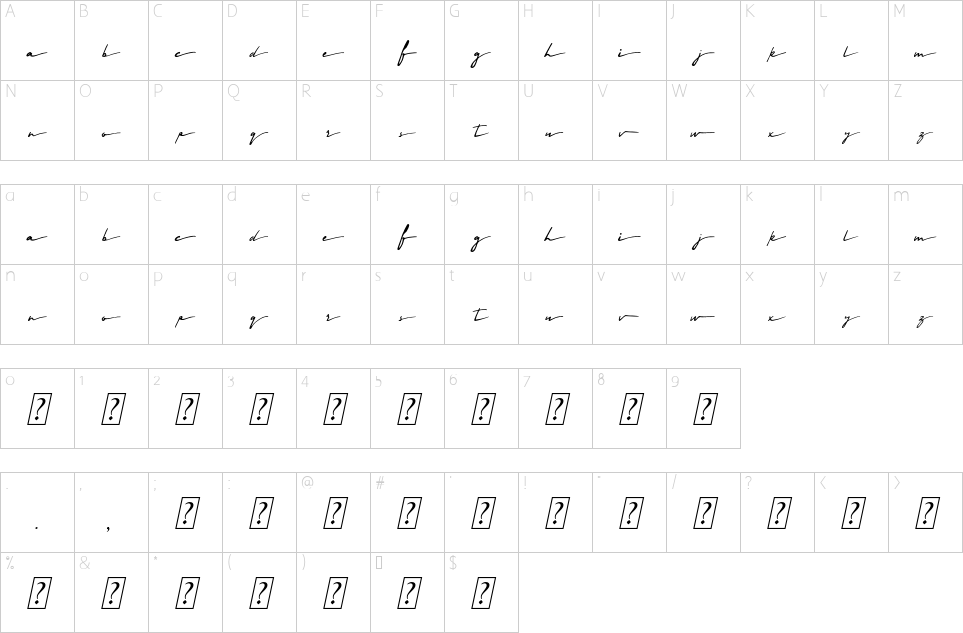
Descubra Midnight Cali, uma fonte criada pelo designer Zansari. Seu estilo elegante, com traços delicados, é perfeito para criar designs modernos e sofisticados. Seu nome refere-se à atmosfera morna e envolvente da meia-noite, uma inspiração para aqueles que desejam um toque de romantismo em suas criações digitais. Com seus 9,078 downloads, Midnight Cali é uma fonte que se tornou uma escolha popular para designers em busca de uma solução gráfica única. Para quem busca adicionar um toque especial ao seu próximo projeto, essa fonte é uma ótima opção para explorar. Download Midnight Cali para Windows e Mac hoje e adicione ao seu arquivo de fontes gráficas.